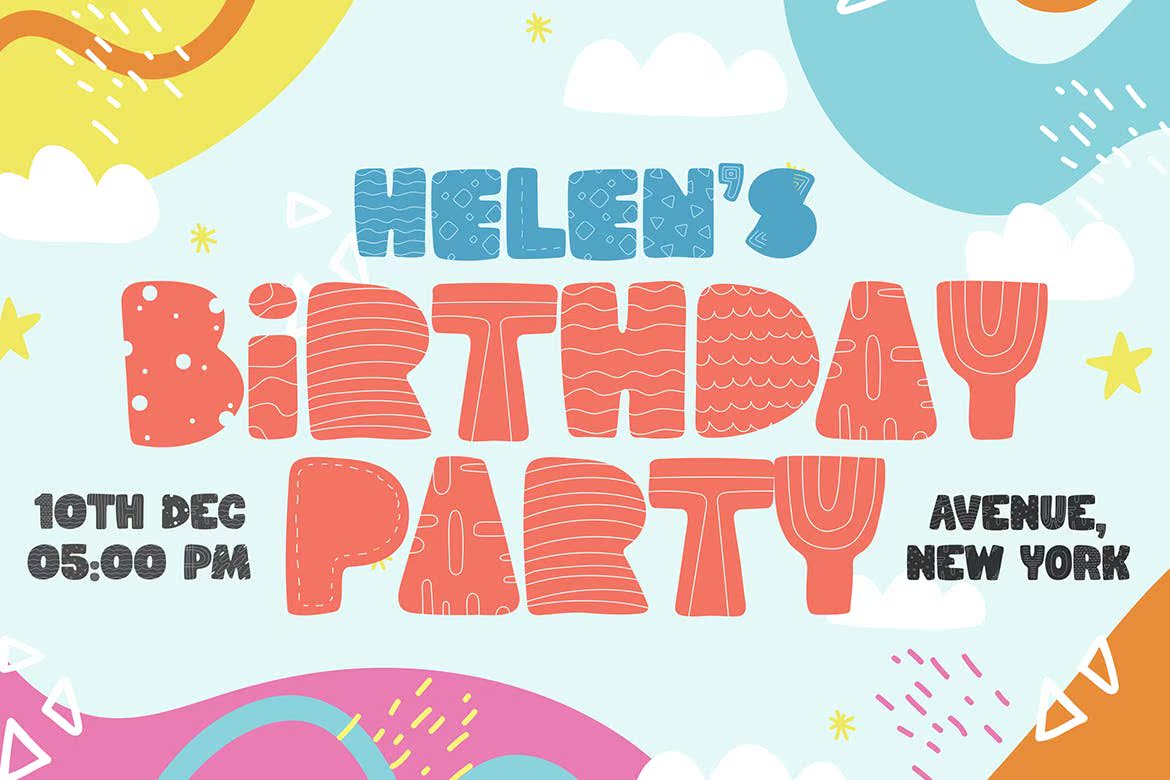
Blocky ShapeWithornament Init.为孩子们提供了一个完美的聚会和一个完美的聚会。适合儿童在线游戏、海报、电影、fastfoodmenu、杂志、YouTube杂志、社交媒体封面,很快…Blocky ShapeWithornament Init.为孩子们提供了一个完美的聚会和一个完美的聚会。适合儿童在线游戏、海报、电影、fastfoodmenu,杂志,YouTubecover,youtubethumbnails,SocialMediaPageCovers和Soon…